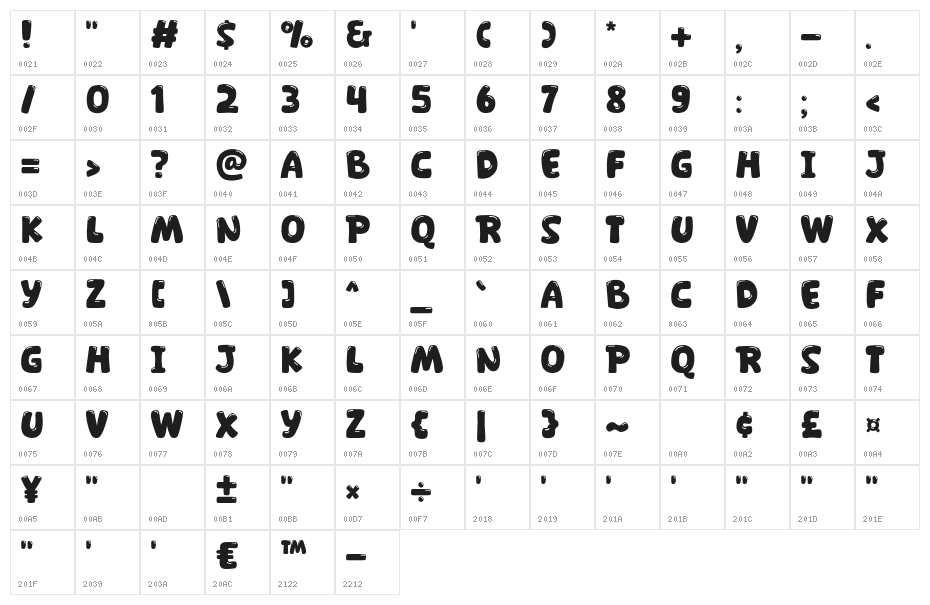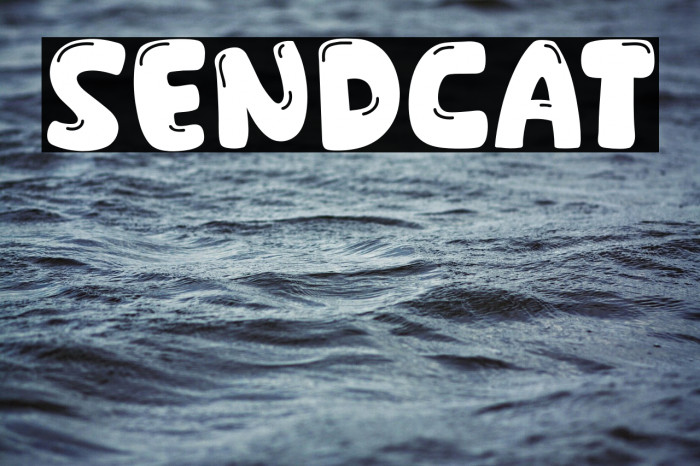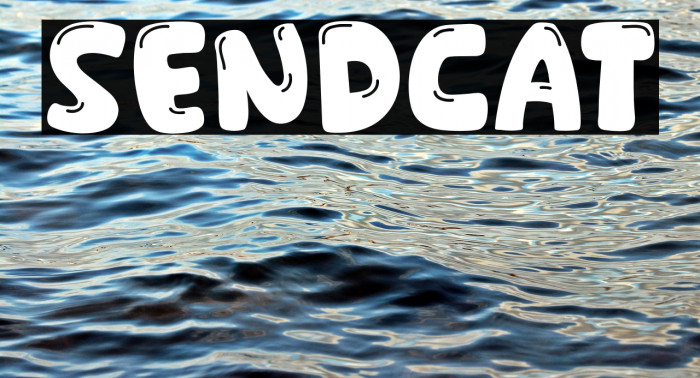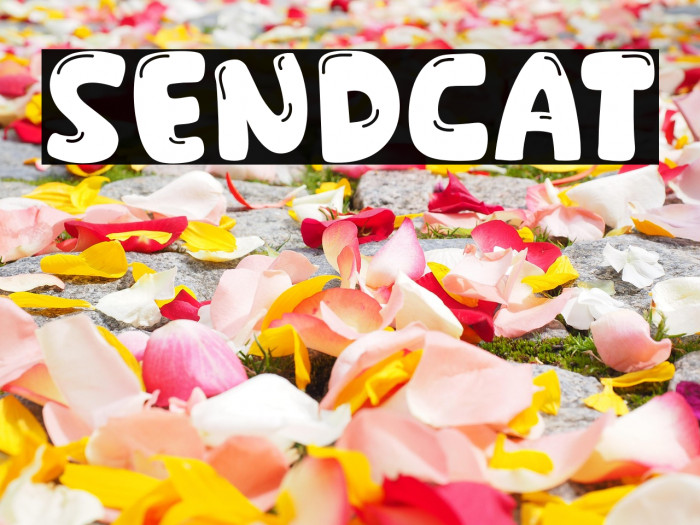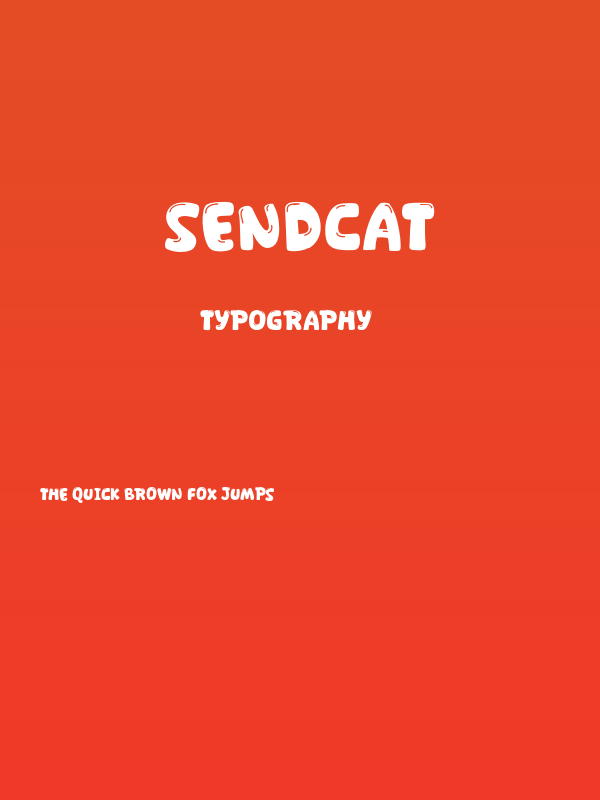
Sendcat Font
| النمط العام | Playful |
| مشاريع مقترحة | Ideal for children's books, playful branding, party invitations, and casual social media graphics. |